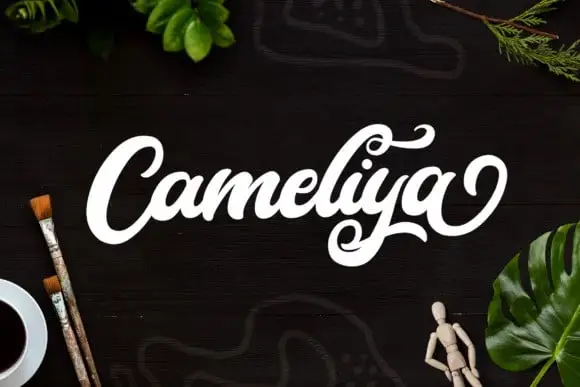
Cameliya Script Font – Fonte Grátis
Cameliya Script Font
A Cameliya Script Font é uma opção perfeita para quem busca adicionar um toque vintage e retro a seus projetos design. Inspirada nas antigos estilos, esta fonte vem com todas as linhas e swashes prontas para uso sem qualquer complicação. A PUA encodagem permite que você facilmente acessa todos os elementos da sua obra de arte, proporcionando um estilo extremamente versátil e atraente. Adicionalmente, a Cameliya Script exibe uma linha de base variável, oferecendo mais opções para diferentes cenários. Além disso, traz características únicas como um gosto vintage e retro, alongados e alternativas incrivelmente belas e ricas em detalhes, garantindo que seus designs sejam sempre memoráveis e impressionantes. Se você está à procura de uma fonte capaz de dar um toque especial a qualquer design, a Cameliya Script é sua escolha perfeita. Crie designs espectaculares utilizando este recurso gráfico único e versátil!